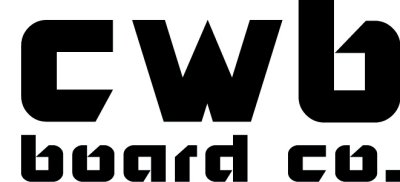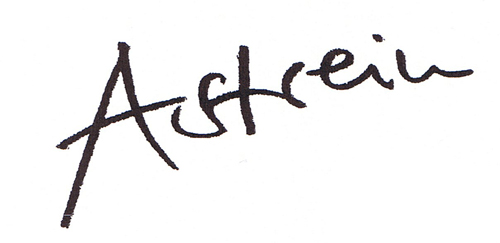
Welche Schriften sind das
Suche dieses zwei Schriften. Hab schon überall gesucht aber nichts gefunden.
Schrift1
Schrift2
Also ich hab ja schon gut gemachte Ligaturen gesehen, aber diese str-Ligatur gibt's wohl nur von Hand.
Oben:
Sie als ganzen Schriftsatz zu finden, wird schwer sein.
Es wird periodisch immer wieder Leute geben,
die mit Lineal und Zirkel versuchen eine Schrift zu zeichnen.
Am "W" kann man sich regelrecht die Finger lecken.